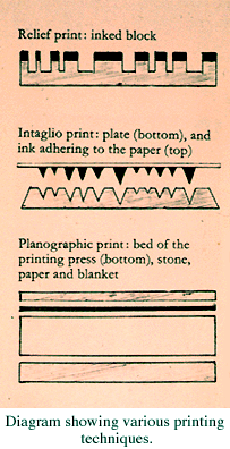
Hipster entdecken Papier
Nichts da, die Sachen von Letterpress seien total up to date, alles Unikate, in kleinen Manufakturen hergestellt. Das habe man auf Instagram gesehen.
Warum? Widerspricht sich doch gar nicht. Viele Sachen, die in dem letzten Jahrzehnten alles so "total up to date waren, sind, oder noch werden, waren es oft auch schon mehrfach in der Vergangenheit und wurden zu biblischer Zeit, im Mittelalter oder bei Indianerstämmen schon mal gemacht. Warum soll die Manufaktur des Herrn Gutenberg so um 1450 mit seinen Unikaten nicht heute wieder total up to date sein?
Dieser (überaus klischeehafte) Text kommt zehn Jahre nach Trendbeginn. Gutenberg hatte mit dem, was heute in Deutschland unter »Letterpress« verstanden wird, nichts zu tun, weil es sich um Prägedruck handelt, nicht um dem Hochdruck vom Bleisatz. Den Hochdruck gab es schon vor Gutenberg, und das Prägen hat er nicht erfunden. »Letterpress« i.e.S. ist in der Tat etwas neues, kam um 2005 herum aus Amerika zu uns: Prägedruck nach digitalen Vorlagen. Der Trend jetzt geht vielleicht langsam wieder in Richtung Bleisatz und Kennerschaft, habe ich den Eindruck. Wenn ich Leuten den Unterschied erkläre, möchten sie jedenfalls heute öfter Bleisatz (also ohne Prägung) als vor fünf Jahren. Daß die Papierdame in dem Artikel »verblüfft« gewesen sei über den Letterpress-Wunsch, klingt in meinen Ohren etwas unglaubwürdig. Manufaktur: Bei Gutenberg standen mehrere Leute an den Setzkästen, die hatten viel zu tun mit der Bibel. Das waren nicht nur drei Setzer, sondern eher ein Dutzend. In den neuen kleinen Manufakturen, die den Trend nutzen, gibt es oft gar keinen Setzkasten mehr, eben weil nur von ein oder zwei Leuten geprägt wird, was mit Bleilettern nicht lange gut ginge.
Typischer Zwischen-den-Jahren-Text aus dem Stehsatz. Möglicherweise eben doch schon ein paar Jahre alt.
»Letterpress« i.e.S. ist in der Tat etwas neues, kam um 2005 herum aus Amerika zu uns: Prägedruck nach digitalen Vorlagen.
Wer hat das vermeintlich so definiert/etabliert? Im Englischen steckt im Begriff Letterpress weder das hier genannte Element des Prägens, noch die Benutzung von digitalen Vorlagen. Letterpress »im eigentlichen Sinne« ist die von dir genannte Beschreibung gerade nicht. Letterpress ist Drucken mit beweglichen Lettern, nichts anderes. Die klassische Gutenberg-Technik.
Wer hat das vermeintlich so definiert/etabliert?
Die Praxis/die Praktiker. Eher weniger vermeintlich als wirklich. Durch Googel-Bildersuche auch leicht zu ermitteln. Im deutschen Sprachraum versteht fast niemand unter Letterpress das traditionelle Handwerk der Schriftsetzer und Buchdrucker, die ohne oder mit schwächster Schattierung drucken. Die sind wirklich selten geworden. Das Wort Letterpress hat hier einen anderen Sinn bekommen als im Englischen. Ein Kollege hat mal versucht, dafür den Begriff »Boston-Style« einzuführen, aber das hat sich nicht durchgesetzt und kam auch zu spät. Zumal man mit Boston-Pressen nicht so gut prägen kann. Der Begriff kam davon, daß anfangs vor allem mit kleinen Pressen von Berufsfremden geprägt wurde. Traditionell war das Prägen eher Sache der Buchbinder oder von Spezialdruckern. Buchdrucker haben nicht geprägt. Auch »American Style« hat mal jemand das Prägen genannt. Das wurde aber auch nix. Heute ist Letterpress Prägedruck, klingt aber besser und irgendwie traditionell. Das einzige, was daran einen traditionellen Zusammenhang hat, ist die Druckmaschine. Nur wird sie eben nicht traditionell benutzt.
Ich fänds ja toll, wenn Letterpress identisch wäre mit der Gutenberg-Technik. Aber meine Setzerei wird mittlerweile von den Prägearbeiten subventioniert. Wie man den Begriff in Amerika heute versteht, weiß ich nicht, nehme aber, daß man inzwischen auch das Debossing damit gleichsetzt. Die Amerikaner unter meinen Kunden verstehen unter Letterpress auch Prägedruck.
Ein bisschen lustig finde ichs ja schon, wenn Martin "Letterpress" als "Prägedruck" bezeichnet. Wenn das jemand anders getan hätte, wäre er sicherlich von Martin belehrt worden, dass "prägen" was ganz anderes ist. Los, Martin, erklär es ihnen nochmal richtig!
"Letterpress" ist nichts anderes als die englische Bezeichnung von "Hochdruck" bzw. der etwas verwirrenden Bezeichnung "Buchdruck" für das Hochdruckverfahren. Höherstehende Teile der Druckform werden mit Farbe versehen und ins Papier gedrückt, tieferstehende Teile werden nicht gedruckt. Dass "Letterpress" für die meisten deutschen Drucker das Wort für Hochdruck mit extrem viel Bumms (geworden) ist hat viel mit amerikanischem Marketing zu tun. Amis, die ja insgesamt recht wenig von solider Berufsausbildung und handwerklichen Regeln halten, haben schon in den 90er Jahren und mit ziemlicher Sicherheit auch davor "letterpress" betrieben und meinten damit durchaus den klassischen Buchdruck. Viele dieser Kollegen waren aber wirklich absolute Laien und haben aus Begeisterung für alte Technik, handwerkliche Selbstfindung, Art&Crafts-Einflüssen und sicherlich ein paar anderen Antrieben mehr einfach mal losgewerkelt und sind dabei häufig (im deutschen handwerklichen Sinne) gescheitert, weil sie eben etliche Druckprobleme "gelöst" haben, indem sie wahnsinnig viel Bumms gegeben haben. Dass dabei aus einer mageren Gill (in Blei) ganz schnell eine breitfette wurde, hat diese Leute nicht gestört. Sie konnten zwar nicht wirklich drucken, hatten aber eine Idee, wie man diese Drucke verkaufen könnte: schon (mindestens) in den frühen 90er Jahren konnte man von diversen Künstlern, Druckern, Möchtegernkünstlern und Möchtegerndruckern in Amerika hochkreative und interessante Drucke kaufen, mit denen man (altes deutsches Druckerwort) "Kartoffeln reiben konnte". Für ziemlich teures Geld, weil diese Drucke ja alle "unique" und "handmade" waren. Das waren die Schlagworte, die "Letterpress"-Drucke verkaufbar machten. Neben der natürlich häufig wilden Gestaltung war aber eben diese Prägung (durch zuviel Druck) ein Alleinstellungsmerkmal und hob sich vom immer arschglatten Offsetdruck ab. Galt gewissermaßen als Beweis für "handmade". Und "unique" wars sowieso, weil fast jeder Druck selbst innerhalb einer Auflage anders aussah. Der Nachteil an der Sache war, dass man dauernd neue Schriften brauchte, weil das teure und oft nicht wiederbeschaffbare Blei natürlich sehr litt. Und irgendwann - auch schon in den 90ern - haben eben diese Amis entdeckt, dass man Letterpress ja auch von Metall-Klischees und Photopolymerplatten drucken kann. Diese Photopolymer (oder Nyloprint-)platten haben den Vorteil, dass sie erstens widerstandsfähiger als Blei, zweitens jederzeit ersetzbar, drittens relativ einfach zu belichten und viertens sogar aus Computersatz/Computergrafik herstellbar sind. Das machte sogar noch mehr Bumms ungestraft möglich und erhöhte den Effekt einer gewissen Dreidimensionalität. Und auch wenn viele dieser Kollegen keine guten Drucker waren, so haben sie zumindest Marketing hervorragend gekonnt und plötzlich war das schwer angesagt. Die Papierindustrie hat sehr schnell mitgezogen und jede Menge sehr voluminöser, relativ weicher Papier mit hoher Grammatur produziert, die dieses Verfahren noch edler aussehen lassen. Und was in Amiland angesagt ist ist, rollt ja als Welle um die Welt ...
Das die Deutschen (Hoch-Drucker) damit ihre Schwierigkeiten hatten war ja klar. Und so hat sich bei den meisten dieser deutschen Kollegen die Unterscheidung in "Letterpress" (drucken mit zuviel Bumms) und klassischen "Buchdruck" ("richtiger Buchdruck" mit sowenig Prägung wie möglich) eingebürgert. Damit stehen wir aber ziemlich allein: die Engländer und Holländer beispielsweise bezeichnen alles, was im Hochdruck gedruckt wird als "Letterpress", egal wieviel Bumms sie geben und egal, obs von Blei oder von Nylo gedruckt wird. Und für viele junge bzw. relativ junge Menschen erscheint "Letterpress" natürlich als neue Erfindung - sie haben den klassischen Buchdruck ja nie wirklich kennengelernt und wenn sie ihn jemals noch kennenlernen für "Letterpress mit erstaunlich wenig Bumms" halten.
Im Übrigen hat Ralf nur teilweise recht: "Letterpress" gibt keinen Rückschluss auf die Art der Satz- bzw. Bildformherstellung, sondern bezeichnet nur die reine Drucktechnologie und hat mit beweglichen Lettern gar nichts zwingend zu tun. Bei "Buchdruck" oder "Hochdruck" ist es ja auch nicht anders: da gabs auch schon neben den beweglichen Blei- und Holzlettern Photopolymerplatten, Metallklischees, Bleischnitte, Holzstiche, Holzschnitte, Linolschnitte, Materialdrucke, Ätzungen ...
Die meisten der momentanen "Letterpress"-Buden haben gar keine Bleisetzerei mehr, sondern machen alles vom Computer auf die Platte. Das hat dann natürlich mitunter kuriose Folgen: ich hatte eine Praktikantin in meiner Werkstatt, die jahrelang in Los Angeles als Letterpressprinterin gearbeitet hat. Die hat bei mir Bauklötzer gestaunt, wieviel Spaß man mit beweglichen Lettern haben kann und welche Möglichkeiten eine auseinandernehmbare und wieder neu kombinierbare Druckform aus Lettern bietet. Kannte sie alles nicht, weil sie jahrelang wie ein stupider Offsetdrucker nur starre, vom Drucker umveränderbare Nyloprintplatten in die Maschine geschoben und mit möglichst viel Bumms ins Papier gepresst hat.
Bei der Lithografie spielt ohnehin Wasser eine große Rolle. Die Druckform auf dem Stein ist mit fetthältiger Farbe aufgebracht. Die druckenden Teile stoßen Wasser ab die nichtdruckenden Teile nehmen Wasser an. Wasser stößt Farbe ab und Fett (Farbe) stößt Wasser ab. Sobald die Form eingefärbt wird stoßen dann die nichtdruckenden Teile die Farbe ab. Nach jedem Druckvorgang wird die Form wieder mit einem nassen Schwamm gewässert. Hier ist dann auch das Papier einer permanenten Feuchtigkeit ausgestzt. Kann bei mehr Durchgängen zu Passerproblemen führen. Spielt aber in künstlerischen Techniken meist keine Rolle.